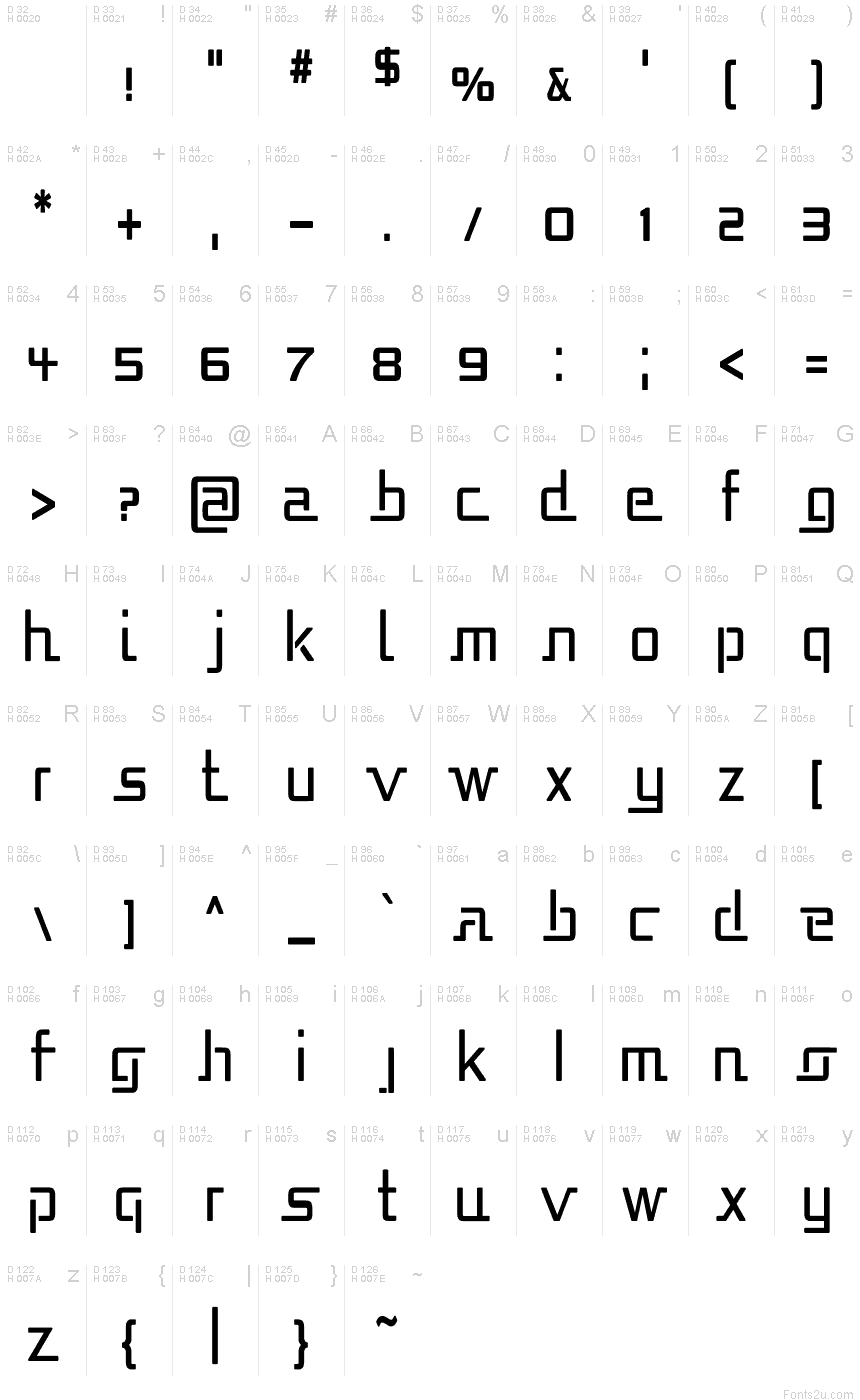
Republika Cnd
Republika Cnd من تصميم Apostrophe هو خط عرض (display) مجاني ومستقبلي ذو إيقاع معياري (modular) وأنيق. تبدو الحروف وكأنها منحوتة من ضربة واحدة مستمرة ومستديرة، حيث تمتزج الزوايا القائمة مع الحواف الناعمة لإنشاء أبجدية "تكنو" نظيفة تبدو هادئة وليست عدوانية.
يناسب هذا الخط الهوية البصرية المستوحاة من الواجهات الرقمية، ومنشورات الموسيقى الإلكترونية، وعناوين أفلام الخيال العلمي، وعناوين الملصقات، والشعارات المدمجة، حيث يمكن للخط المجاني أن يضفي طابعاً اصطناعياً دون أن يكون مزعجاً بصرياً. ولأن أشكال الحروف تتداخل وتترابط بإحكام، فهو يعمل بشكل جيد أيضاً في الشعارات المركبة (Monograms)، والنصوص القصيرة على الأغلفة، واللافتات التي تتطلب لمسة رقمية هادئة.